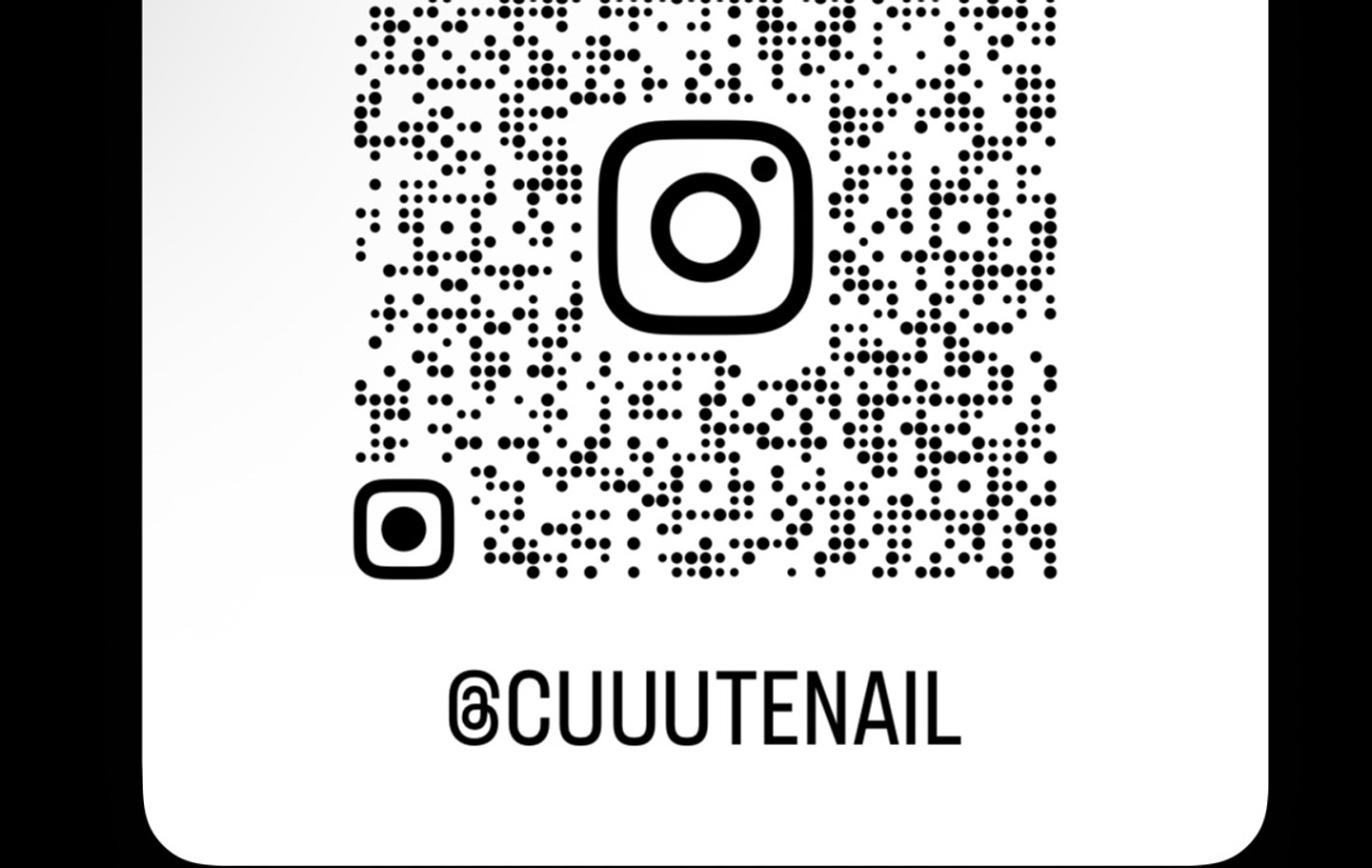
Times New Roman폰트인데 id에서 치니까 소문자가 더 폰트도 두껍게 나오고 폰트도 Times New Roman 맞나요? b가 좀 다른데;
위 아래 폰트 둘 다 궁금해용..!!
뭘까용
ㅅㄷㄱㄹ에 찾아보나 and사랑스러워 폰트라는 데 다르거든요ㅠㅠ 알려주세요
아무리 찾아도 안나와요우ㅜㅜ
TVING 포핸즈 쇼츠에서 본 자막인데 이 폰트 뭔지 아시는분!!ㅠㅠ
이거 무슨 폰튼가요
뭘까요? ㅠㅠ
폰트 알려주세용
보아 밀키웨이 음악캠프 자막 폰트 뭘까요? ㅠㅠ
갤럭시 '한편의영화' 폰트랑 비슷해요 근데 그거랑은 ㅎ모양이 다르네요 ㅠㅠ 아시는분 계실까요
폰트 무슨 폰트인지 알려주세요!!
폰트 정보 알고싶어용
아일릿 만찬가 커버에 나온 일본어 자막인데 폰트가 어떻게 될까요??